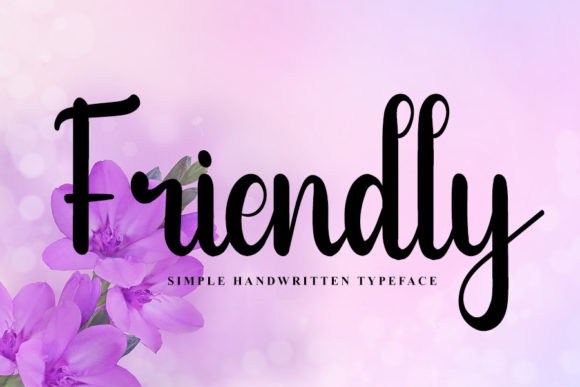
Friendly
หากคุณกำลังมองหาเนื้อหาคุณภาพสูงเช่น Friendly แพ็คเกจพรีเมียมนี้เป็นตัวเลือกที่ยอดเยี่ยมสำหรับโปรเจ็กต์สร้างสรรค์ของคุณ
ไม่ว่าคุณจะสร้างผลิตภัณฑ์ POD (Print on Demand) คำเชิญงานแต่งงาน หรือกราฟิกโซเชียลมีเดีย Friendly ก็เหมาะสมอย่างยิ่ง